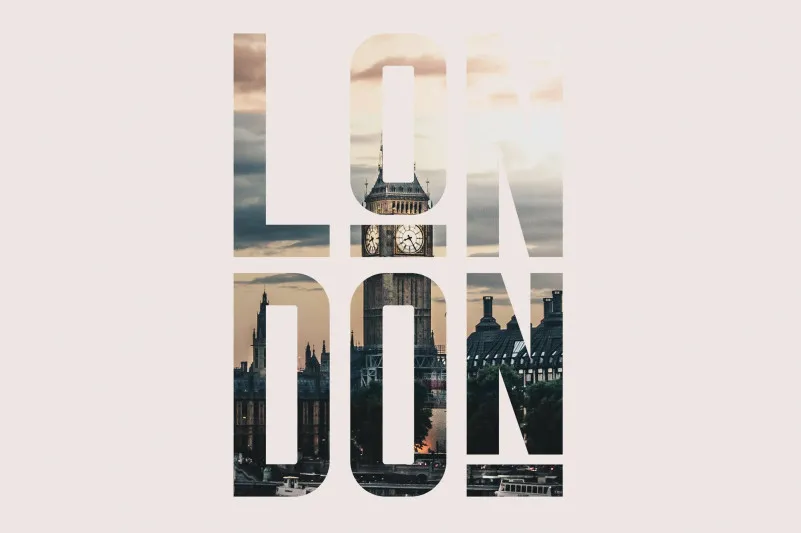
A Harrison Retro Font é uma seleção perfeita para quem busca um estilo retro e bold em seus projetos digitais. Esta fonte vem no formato latino e cyrillic, oferecendo suporte a ambos os alfabetos, com versões regulares, marcantes e com toques ásperos para garantir que todas as nuances da letra sejam capturadas. Além disso, ela inclui suporte multilíngue, tornando-a perfeita tanto para projetos em inglês quanto naqueles que trabalham com outros idiomas. Com sua abrangência tão ampla e seu poder de adaptação para todos os tamanhos, a Harrison Retro Font é uma excelente escolha se você está buscando um tipo de fonte moderno que carrega o peso nostálgico dos anos 80 e 90. É perfeito tanto para aplicativos de design de sites quanto para criação de material gráfico em geral, garantindo não apenas um visual atraente, mas também uma versatilidade incomparável.